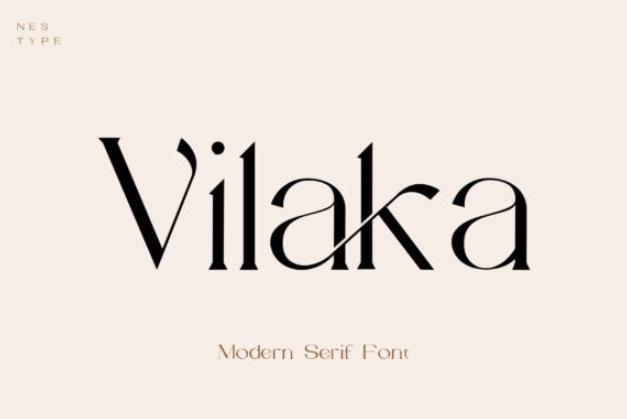
[Creativefabrica] Vilaka Font (Nest Studio)
Vilaka - это модный современный шрифт с засечками, который выглядит свежо и красиво. Это очень универсальный шрифт, который хорошо работает как с маленькими, так и с большими размерами. Идеально подходит для редакционных проектов, логотипов, упаковки продуктов.